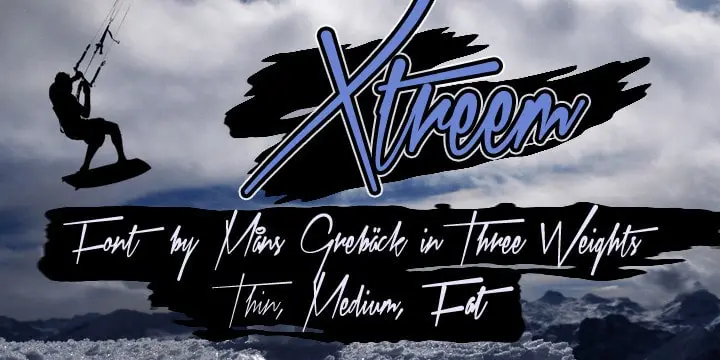
A Xtreem Font é uma elegante fonte script criada pelo designer Hamilton, perfeita para adicionar um toque sofisticado a qualquer projeto visual. Com linhas delicadas e formas arredondadas, essa fonte traz à vida um estilo gráfico que combina charme com flexibilidade, ideal tanto para criações digitais quanto impressas. Se você está procurando por uma fonte que possa se destacar em qualquer ambiente de design, a Xtreem é definitivamente o item a ter na sua biblioteca de recursos. Para adquirir esta bela fonte e obter um licenciamento comercial, visite o site oficial em: http://www.mansgreback.com/xtreem. Não hesite em explorar os infinitos possíveis desta fonte única que certamente enriquecerá seu trabalho de design.